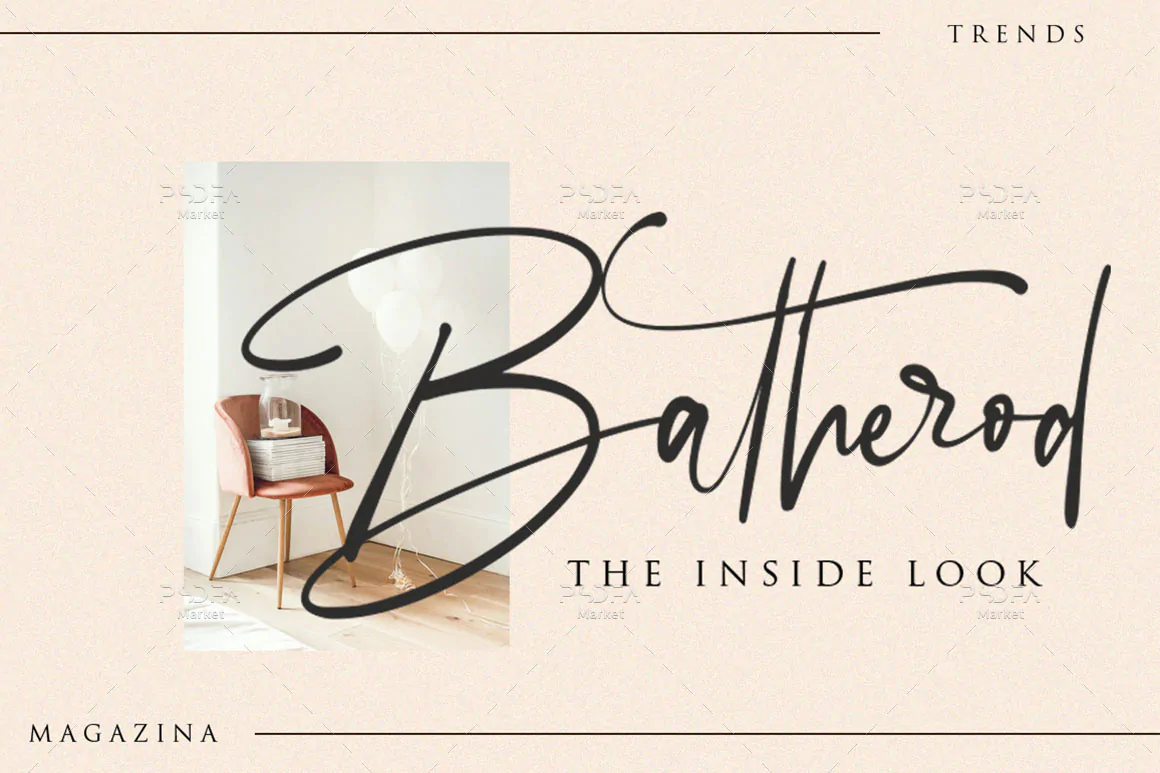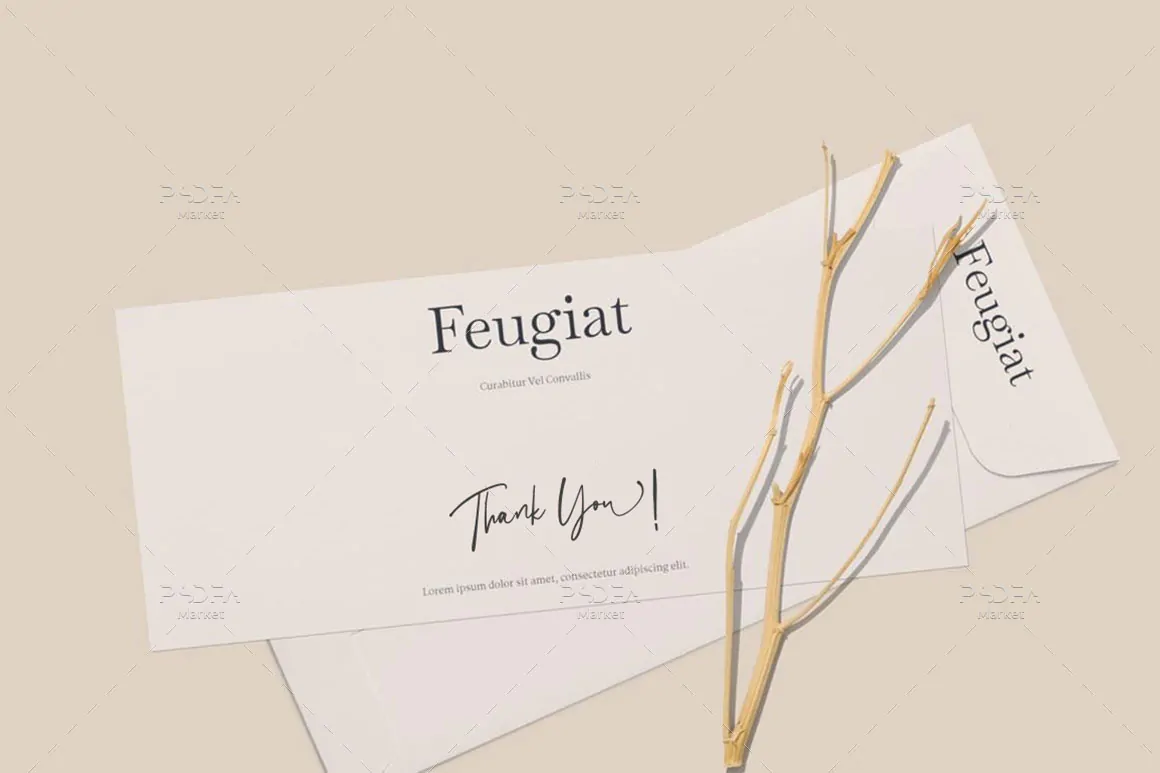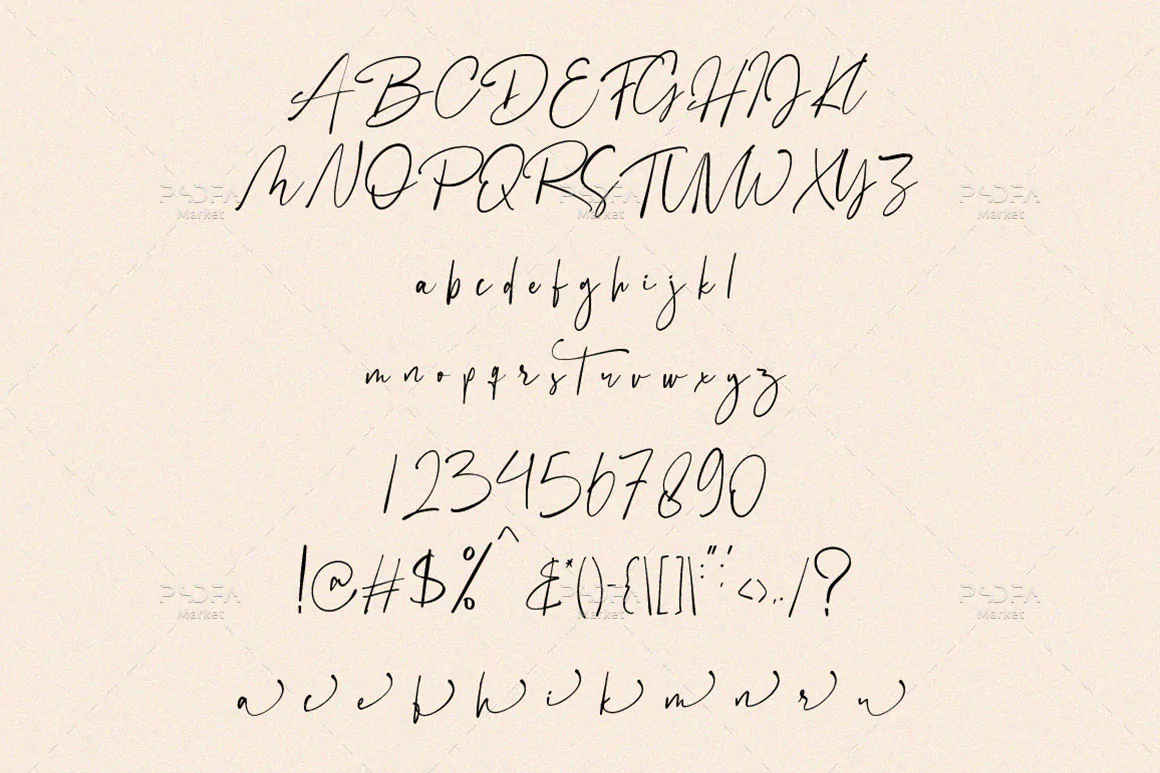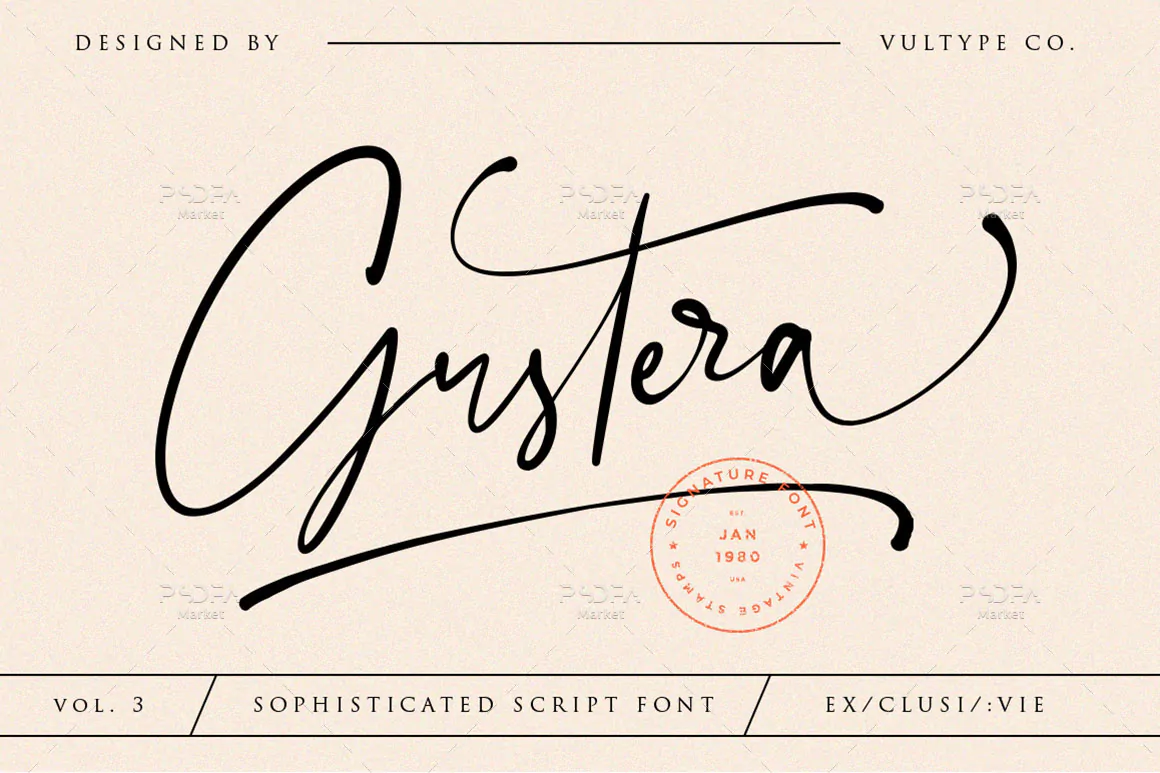
فونت دستنویس باریک Gustera
فونت دستنویس باریک
فونت دستنویس باریک Gustera یک اسکریپت فونت فوق العاده زیبای انگلیسی است که مناسب جهت استفاده در طرح و پروژههای گرافیکی مختلف میباشد. این فونت زیبا با وزن معمولی طراحی شده است که میتوانید از آن در طراحی انواع کارت تبریک، طرحهای رمانتیک و عاشقانه، بسته بندی محصولات، پوستر، قاب عکس، پست و استوری رسانههای اجتماعی و … استفاده کنید.